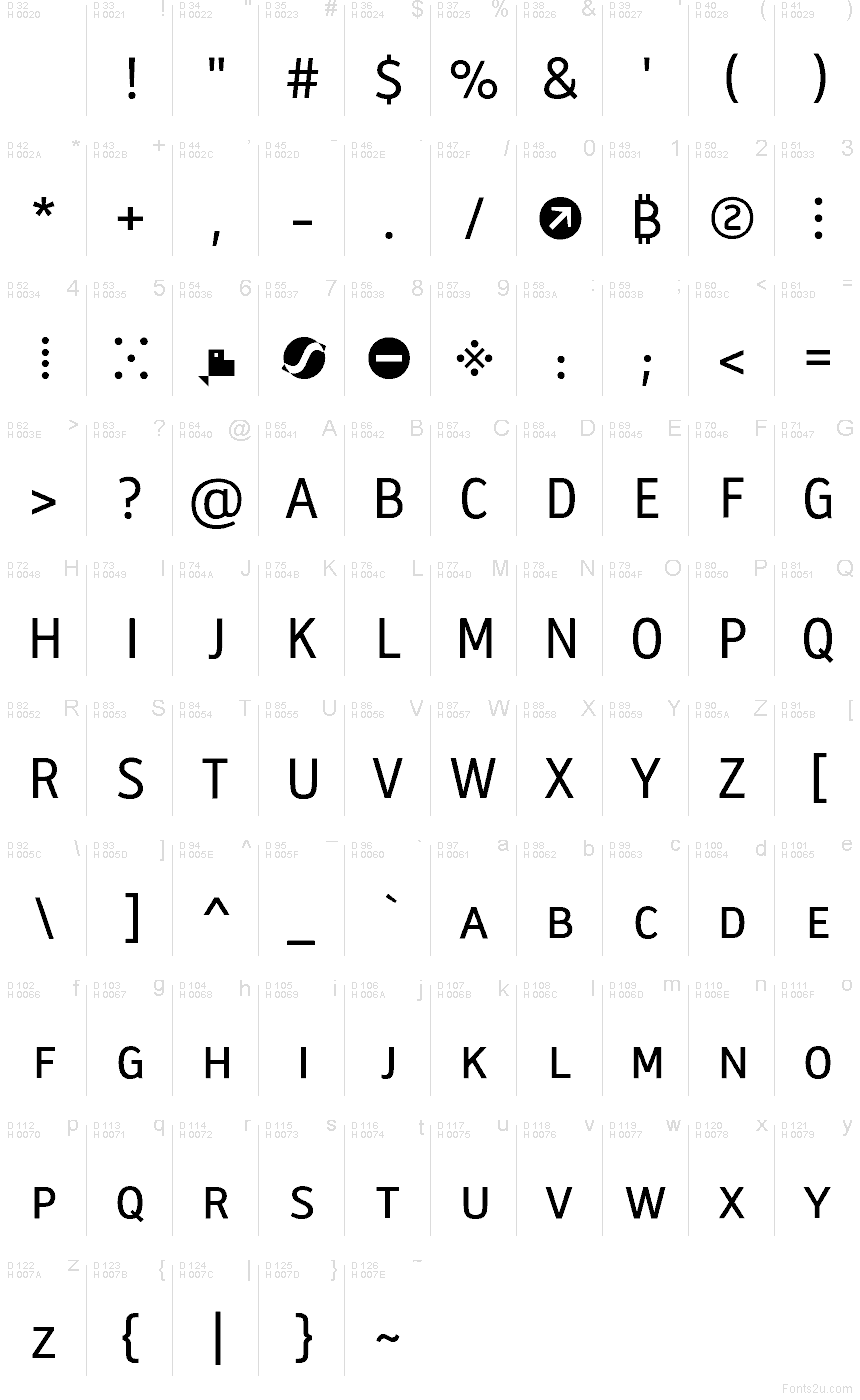
Biotrip Caps, di deFharo, è un font sans serif geometrico in maiuscolo, gratuito, con un tono fresco e leggermente futuristico. Le lettere hanno un aspetto essenziale e ricercato, costruito con forme rotonde pulite e tagli netti che mantengono il ritmo aperto, mentre alcune giunture più affilate evitano che il design risulti banale.
Si inserisce perfettamente in progetti di branding, titoli di locandine, artwork musicali, titoli video e packaging tecnologici in cui si desidera un tono moderno senza cadere nei cliché della fantascienza. Essendo un font gratuito, è ideale anche per brevi testi di copertina, monogrammi e marcature per interfacce, poiché le maiuscole presentano una silhouette semplice che rimane impressa in contesti brevi e d'impatto.
Biotrip Sans Caps is a multipurpose typeface, refined down to the last detail. It includes seven weightsLight, Regular, Medium, Semi Bold, Bold, Extra Bold, and Blackthat allow for the creation of solid, adaptable, and expressive visual systems.
Each variant has been carefully designed to preserve the humanist essence of Biotrip Sans, with the authority of capital letters.